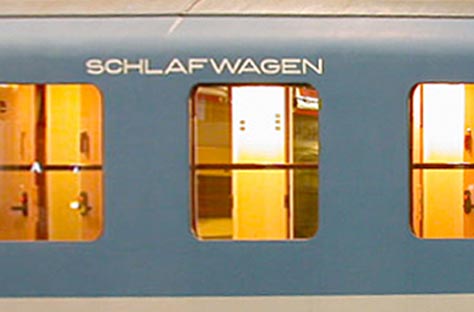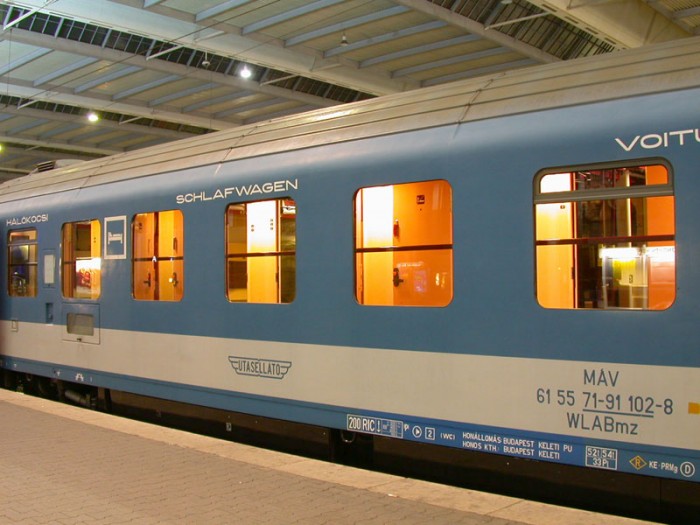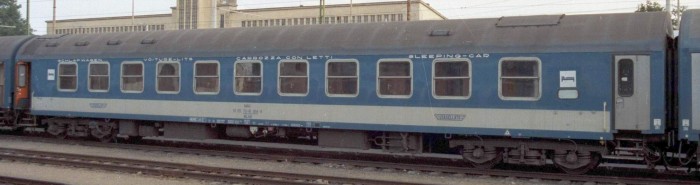
Welche Schrift ist das? (Schlafwagen)
ich suche eine der hier gezeigten Schriftarten.
Über den Fenstern ist der Schriftzug Schlafwagen in unterschiedlichen Sprachen zu sehen.
Wer kennt diese Schrift. für ein Freeware-Projekt suche ich wenn es geht eine Freeware derivat aber der Name der Originalschrift interessiert mich natürlich auch.
besser gehts wohl nicht mit der Bildentzerrung
Geht schon, bringt aber in Hinsicht auf die Identifizierung der Schrift nicht viel.
Hallo, danke für eure schnellen Antworten. Nun die MAV wird das vermutlich selbst nicht wissen, da Beschriftungen bereits vorgefertigte Vorlagen sind. Auch andere Bahngesellschaften des ehemaligen Ostblocks hatten diese Schrift verwendet.
Ausnahme ist da wohl die Mitropa.
dessen Schrift suche ich auch noch. (über den Fenstern)
Ihr habt da sicher recht, dass diese Schrift nur für einen bestimmten Zweck entworfen wurde.
Beispiele gibt es da ja viele.
Jau das ist wohl die beste Wahl..wenn man diesen Font noch staucht (bitte nicht hauen ;-) ) kommt man auch an die Mitropaversion.
Oder geht es hier um die Renovierung von Museumswagen? So eine Anfrage hatte ich vor einiger Zeit im Zusammenhang einer Anpassung der DIN 1451 in einigen wenigen Buchstaben bei den Anschriften eines alten Reichsbahn-Wagen.
Auch beim Mitropa-Wagen scheint mir die lateinische Schrift auf der DIN zu basuieren, jedoch irgendwie zwischen Mittel- und Breitschrift zu liegen, also auch speziell gezeichnet. Allerdings wundert mich die doch extrem in ihrern Formen abweichende kyrillische Schrift mit starkem Strichkontrast.
Man darf aber eines nicht vergessen: Die weitaus meisten Fahrzeuganschriften, gerade bei Schienenfahrzeugen stammen aus einer Zeit, in der es Computergrafik, so wie wir sie heute täglich verwenden, noch nicht gab. Anschriften für eine recht große Fahrzeugflotte waren daher so entworfen, dass sie mit den damals üblichen Methoden von durchschnittlichen Lackierern angebracht werden konnten, und man hinterher eben keine eigenen Handschriften daraus ablesen kann. Daher wurden typografische und gestalterische Feinheiten bewusst außer Acht gelassen, und die Schrift zumeist auf eine einfache Konstruktion mit Zirkel und Lineal beschränkt. Von einem Werkzeug, wie einen Schneidplotter konnte man nicht einmal träumen. Druckbuschstaben waren entweder in Blei gegossen, oder in Plakatgröße in Birnenholz gefräst.
Fahrzeuganschriften wurden aber zumeist am Zeichenbrett von Hand entworfen, und dann auf eine, direkt mit Zuckerwasser auf den zuvor aufgebrachten Grundlack geklebte Stanniol-Folie durch gepaust. Anschließend wurden die Buchstaben freihändig mit einem Federmesser aus der dünnen Zinnfolie herausgeschnitten, sodass hierdurch die Schablone zum Lackieren entstand.
Ich habe diese Technik noch im täglichen Einsatz erlebt, sie wurde in den 1970er Jahren noch gelehrt.
Mir kommt es so vor, dass die Schriften der Ungarische Eisenbahn auf die Schriften der DIN 1451 basieren. Also Engschrift, Mittelschrift und Breitschrift. Formal gesehen haben die drei nie richtig zusammengepasst. Daher liegt es auf der Hand dass es sich hierbei, je nach dem was für Kriterien man anwendet, um veränderte, verbesserte oder vielleicht sogar verschlimmbesserte Version der DIN Schriften handelt. Die Deutsche Reichsbahn führte auf den Personenwagen der Rheingold-Züge in den 1930er Jahre einen DEUTSCHE REICHSBAHN-Schriftzug der vielleicht Modell stand für die DIN Breitschrift. Die RHEINGOLD-Schriftzüge selbst waren eckiger, in etwa wie die spätere Eurostile. Ich kann es mir gut vorstellen, dass andere Eisenbahngesellschaften bzw. sich gerne an diese Schriftbilder orientiert haben.
Es gibt die Schlafwägen auch in anderer Beschriftung, falls das von Interesse ist:
Ja von interesse ist alles was das Thema Typo und Eisenbahn betrifft.
Vielleicht kennt ja einer "deine" Schriften. Oder du weisst es selbst.
Geht schon, bringt aber in Hinsicht auf die Identifizierung der Schrift nicht viel.
vielen Dank Paschulke, besser gehts da nicht mehr
Doch, geht. Denn Tonneneffekt hätte man auch noch korrigieren können. Aber irgendwie hat da bei mir grade der Objektiv-Korrektur-Filter gehangen.
Darf ich mal fragen, was Du vor hast? Willst Du Deine Modellbahn nur noch im Dunkeln fahrn lassen? ;-)
hallo..ja na klar darfst du. ich entspanne mich am Computer an einer Eisenbahnsimulation und dort verwendete Wagen sollen umlackiert werden (Auftraggeber Ich selbst ;-) ). Laut Lizensbestimmungen und Copyright nur für den eigenen Bedarf oder mit Absprache des Entwicklers/Erstellers.
Aber in der Tat gibt es Modelleisenbahner die das selbe mit ihren Modellen machen und sogar Abziehbilder Kaufen um ihre Modelle so genau wie möglich zu beschriften.
Ich Verbinde zwei Berufswelten mit einander. Als gelernter Eisenbahner und auf dem zweiten Bildungsweg Als Mediengestalter mit typografischer Ausbildung, 3D-Designer... Da sind diese Fragen Typo und Eisenbahn immer Interessant. Aber sicher nicht nur mit diesem Background. Früher gabs ja bei den Jungs nur zwei optionen Carrerabahn oder Modeleisenbahn oder nichts von beidem.
Übrigens: auch wenn diesen Beschriftungen keine Satzschriften zu Grunde liegen. Es gibt dann umgekehrt aber Satzschriften, die von den Zugbeschriftungen abgeleitet wurden.
Hallo Ralf, Ah siehst du ich hatte bei meiner Morgendusche genau den Verdacht...und siehe da..du bestätigst mir das. Der Peter mit seiner Midroba..auch eine sehr schöne Arbeit ...hat diese für den kleinen Geldbeutel nachempfunden.